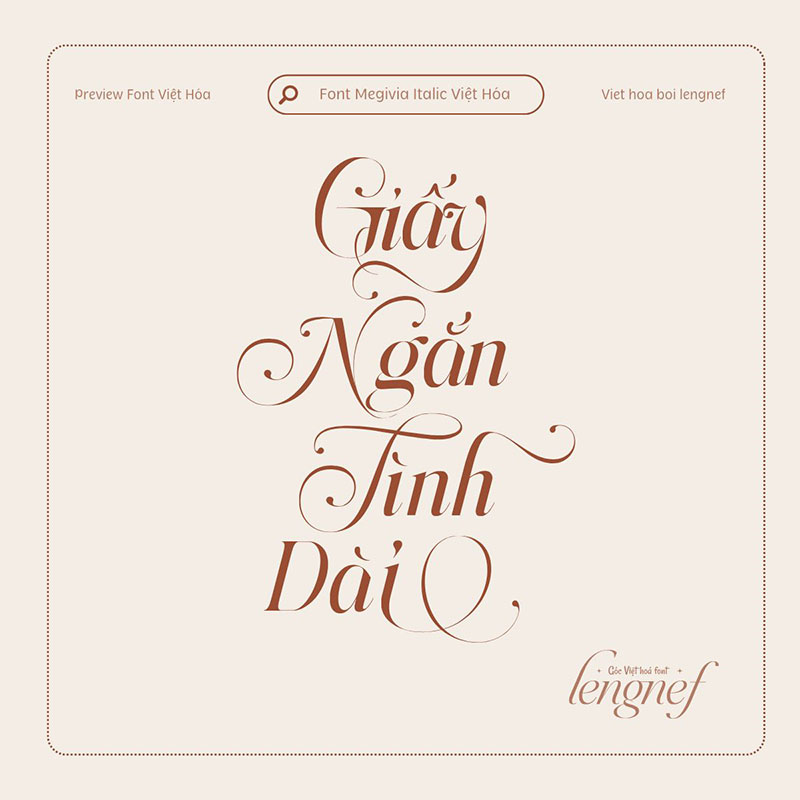
Share Font 63 || LF Megivia Italic
- Tác giả: Ikhsan Maulana
- Việt hóa: lengnef
Phông chữ này có 6 kiểu mỗi kiểu đều được chế tác với bộ chữ ghép phong phú và các biến thể kiểu dáng, Megivia mang đến cho bạn sự linh hoạt sáng tạo không giới hạn. Phù hợp cho bao bì thời trang, thương hiệu cao cấp, thiệp mời, tiêu đề và logo, Megivia luôn mang lại kết quả mạnh mẽ nhưng duyên dáng.